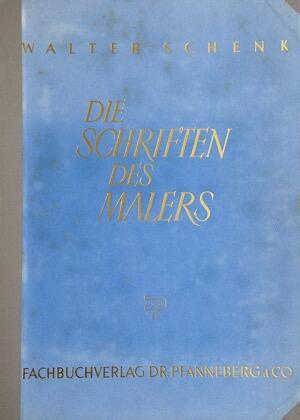
Die Schriften des Malers ist eine großformatige Mappe mit »Vorlagen und Anleitungen für das Maler-, Lackierer- und Schilderhersteller-Handwerk«. Die Mappe enthält ein 124 Seiten starkes Lehrbuch sowie 50 separate Tafeln, die hauptsächlich Schriftmuster enthalten.
Das Buch beschreibt alle Aspekte des Schildermaler-Handwerkes – von stilistisch/historischen Grundlagen der Schrift bis hin zu allen gestalterischen und technischen Belangen beim Entwurf und der Umsetzung von Schrift-Beschilderungen. Die Schrift-Vorlagen-Tafeln sind auf hohem Niveau geschrieben bzw. gezeichnet und stellen eindrucksvoll die Schriftgestaltung im deutschen Schildermaler-Handwerk in der Mitte des 20. Jahrhunderts dar.
Inhalt des Buches:
- Die Geschichte unserer Schrift
Die Grundlagen der Schriftgstaltung
- Geschriebene und gezeichnete Schriften
- Das Skelett der Buchstaben
- Der optische Ausgleich
- Statik und Dynamik der Buchstaben
- Der Buchstabenabstand
- Der Wortabstand
- Der Zeilenabstand
- Die Einteilung
[*]Wahl und Anordnung der Schrift
- Die Anpassung an Zweck und Umgebung
- Die Textgestaltung
- Die Rechtschreibung auf Schildern
- Die Schriftwahl
- Grundsätze für die Mischung
- Die Lesbarkeit
- Das Größenverhältnis von Schrift und Fläche
- Die symmetrische Anordnung
- Die asymetrische Anordnung
- Der Schriftblock
- Die Kontraste
- Die senkrechte Zeile
- Die gebogene Zeile
- Die schräggestellte Zeile
- Die negative Zeile
[*]Proportionsänderungen
- Die Bildung der fetten und der mageren Form
- Dekorative Veränderung der Schrift
- Die Sperrung
[*]Die farbige Gestaltung
- Die Tonwerte
- Die Farbe der Schrift im Innenraum
- Die Farbe der Außenbeschriftung
- Der Einfluß der Farbe auf die Lesbarkeit
[*]Die dekorative Ausgestaltung der Schrift
- Allgemeines
- Die Konturen
- Der Schatten
- Die Belebung der Buchstabenschenkel
- Die Prismaausführung
[*]Bildhaft dargestellte Schrift
- Allgemeines
- Die plastische Schrift
- Plastische Schrift in frontaler Perspektive
- Perspektivische Schrift in der Übereck-Ansicht
- Perspektivische Schrift auf regelmäßig gekrümmten Flächen
- Die Schrift auf unregelmäßig gekrümmten Flächen
[*]Schriftübungen
- Der Nutzen des Übens
- Vorbereitungen zum Üben
- Schreibgerät und Schreibflüssigkeit
- Das Üben mit der Feder
- Das Üben mit dem Pinsel
[*]Die Technik
- Werstatt und Material
- Die Skizze, der Entwurf
- Die Pause
- Die Aufzeichnung
- Schreibgerät und Schreibtechnik
[*]Unsere Alphabettafeln
- Anleitung zu ihrer Anwendung
- Die Redis-Grotesk
- Gotische Schrift I
- Gotische Schrift II
- Antiqua
- Antiqua-Kursiv
- Unziale
- Schwabacher
- Kanzleischrift
- Deutsche Schreibschrift
- Blockschrift
- Blockantiqua
- Wiener Blockschrift
- Steile Blockantiqua
- Römische Kapitalschrift
- Mediäval-Antiqua
- Klassizistische Antiqua
- Egyptienne
- Steile Antiqua
- Textur
- Fraktur
- Rotunda
- Runde Kursiv
- Fette Kursiv für Schilder
- Neuzeitliche Antiqua für Schilder
- Freie Wechselzugblock
- Freie Schnurschrift
- Lateinische Piselschrift
- Plakat-Bandzugschrift
- Filmschrift
- Werbe-Kursivschrift
- Modeschrift
- Englische Schreibschrift
- Feine Kursiv
- Italienne-Formen
- Freie Plakatschrift
- Antiqua für dekorative Wandschrift
- Neuzeitliche Unzialschrift
- Kurrentschrift
- Barockschrift
[*]Die Anwendungsgebiete der Schrift
- Die Wandbeschriftung im Innenraum
- Die Fassadenbeschriftung
- Der Giebel
- Das Plakat
- Das Schild
- Das Glasschild
- Das Glastransparent
- Die plastischen Buchstaben
- Die Leuchtbuchstaben
- Die Gestaltung der Ladenfront
- Der Lieferwagen